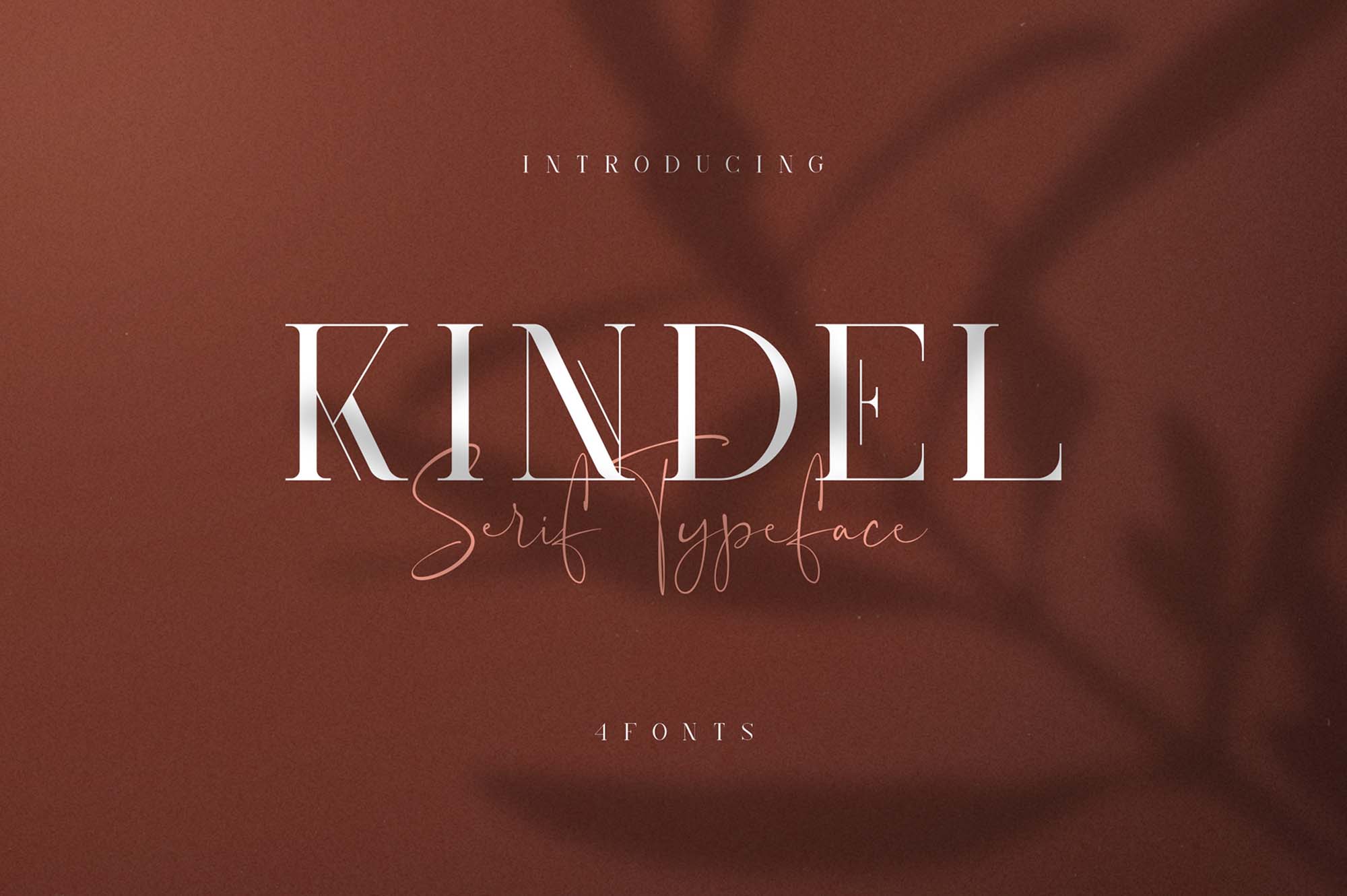
Kindel Serif Typeface – Download Grátis
Kindel Serif Typeface é uma tipografia de serif que oferece um toque de elegância moderna. Suas linhas suaves e detalhes sutis criam um equilíbrio perfeito entre sofisticação e contemporaneidade. Ideal para quem busca um toque elegante em seus designs, este tipo de fonte oferece uma linguagem fluida e confiante que se adapta perfeitamente para gráficos de alta qualidade. Perfeito para um mockup, o Kindel Serif Typeface proporciona um visual atraente e profissional, ideal para qualquer tipo de projeto que exija um toque de sofisticação.